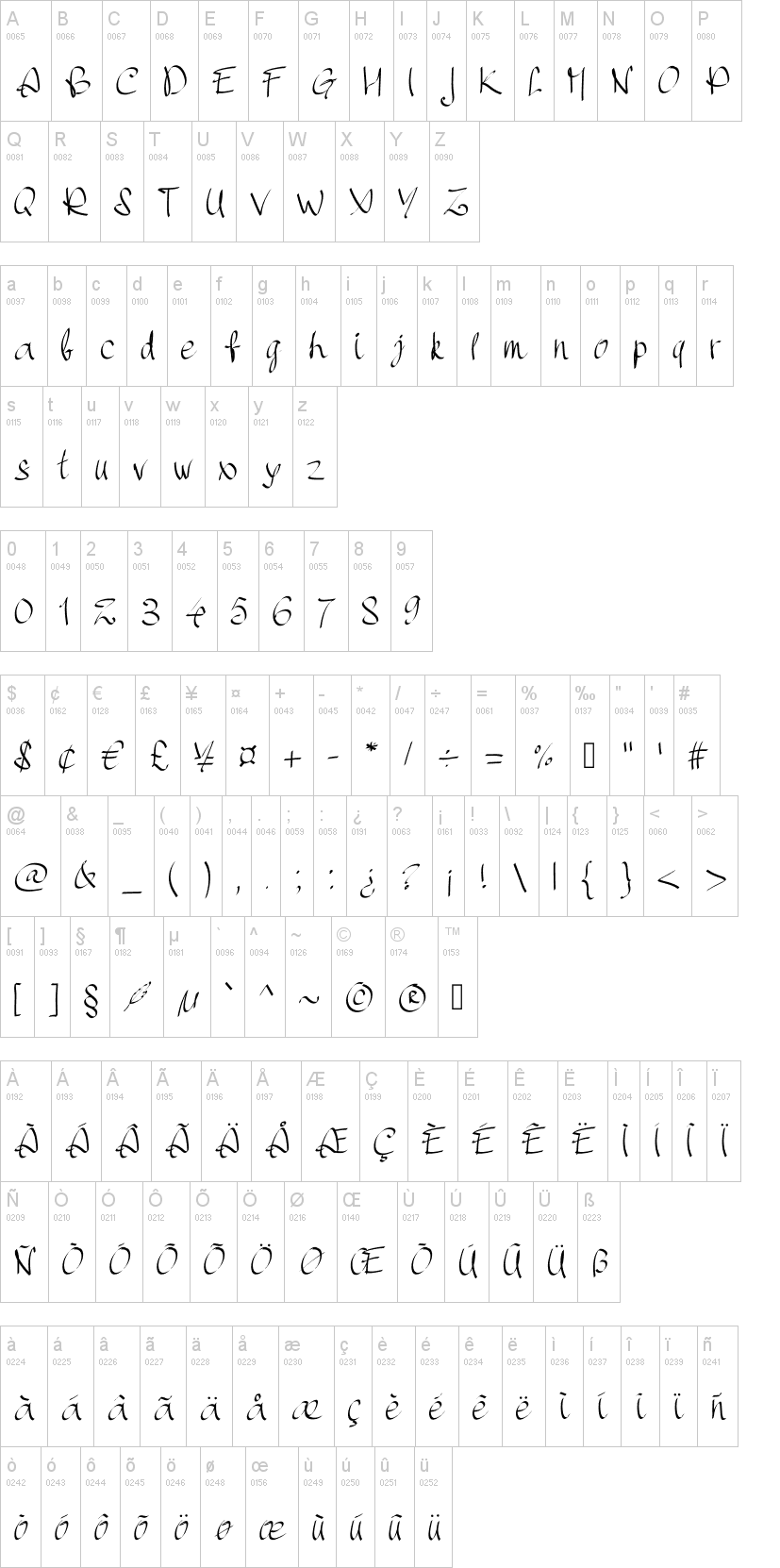
PW Handscript是一种手写风格的字体,由设计师Päivi Wong创造。这种字体通常用于印刷设计,特别是那些需要手写风格的项目。PW Handscript字体有一种自然、随意的感觉,使得它非常适合那些需要表现个性、温馨或者接近人们的情感的设计项目。 PW Handscript字体有两种版本:正常和倾斜。正常版本的字母和符号是直立的,而倾斜版本的字母和符号则向左倾斜,使得它看起来更加自然,就好像是在手写一样。此外,PW Handscript还包括了大量的特殊符号和装饰性符号,这使得它非常适合那些需要添加额外风格的设计项目。 总的来说,PW Handscript是一种非常实用的字体,可以用于各种不同的设计项目,特别是那些需要表现个性、温馨或者接近人们的情感的项目。内容介绍
PW Handscript是一款非常不错的手写艺术字体,具有很好的视觉感,适合于文化类的宣传设计、商业类品牌的广告和产品包装设计以及个性化文字排版等较多场景。